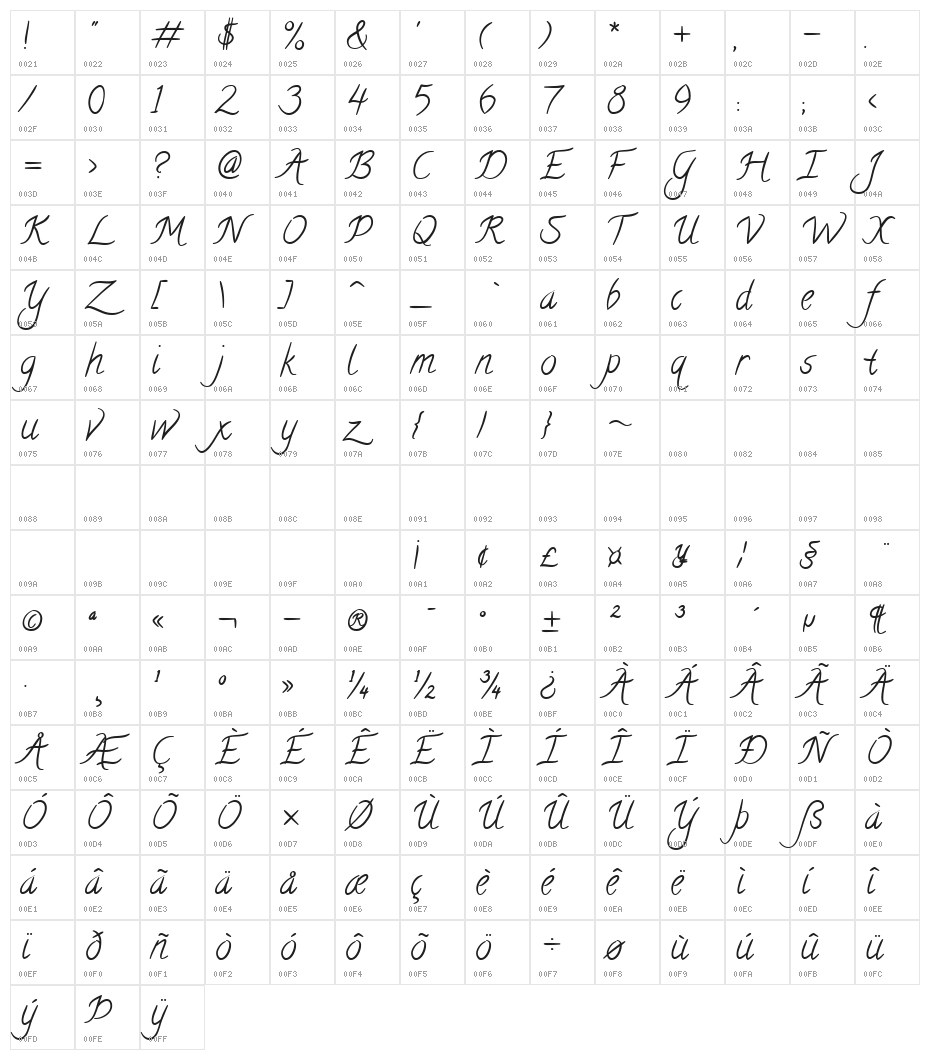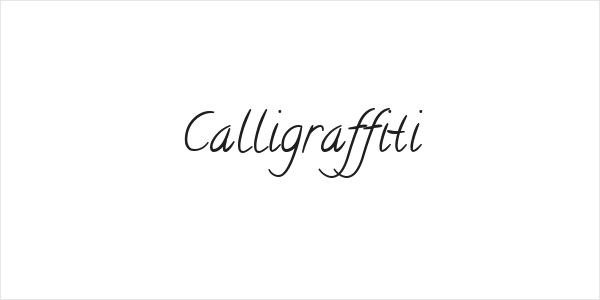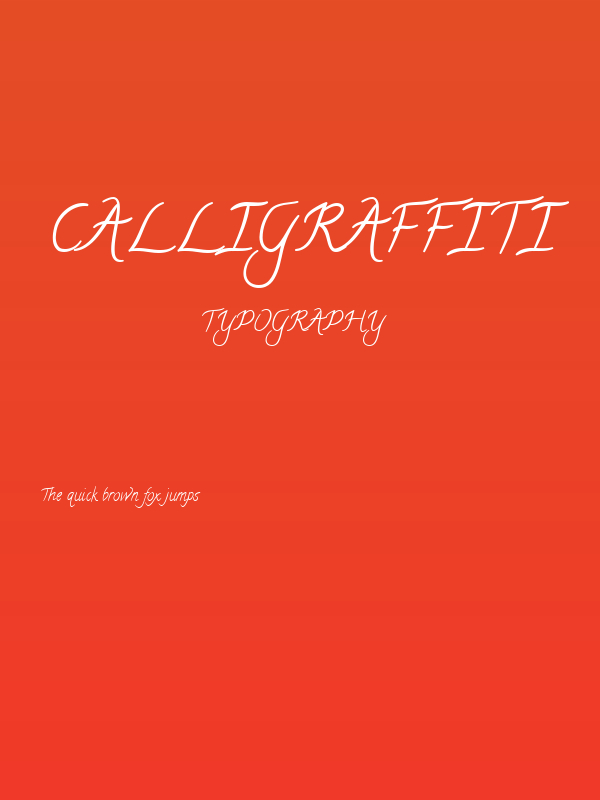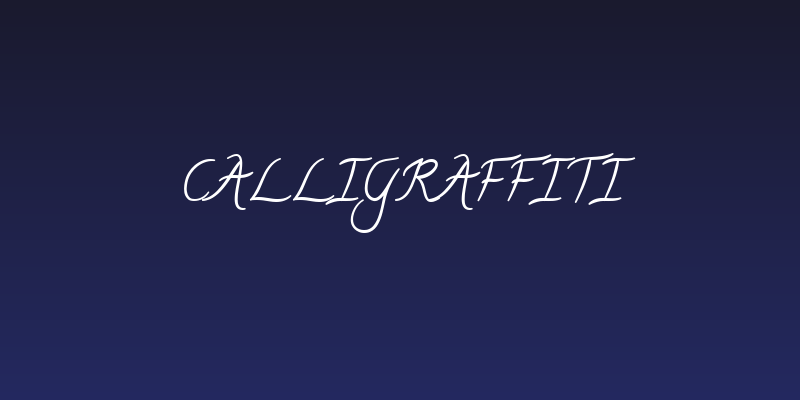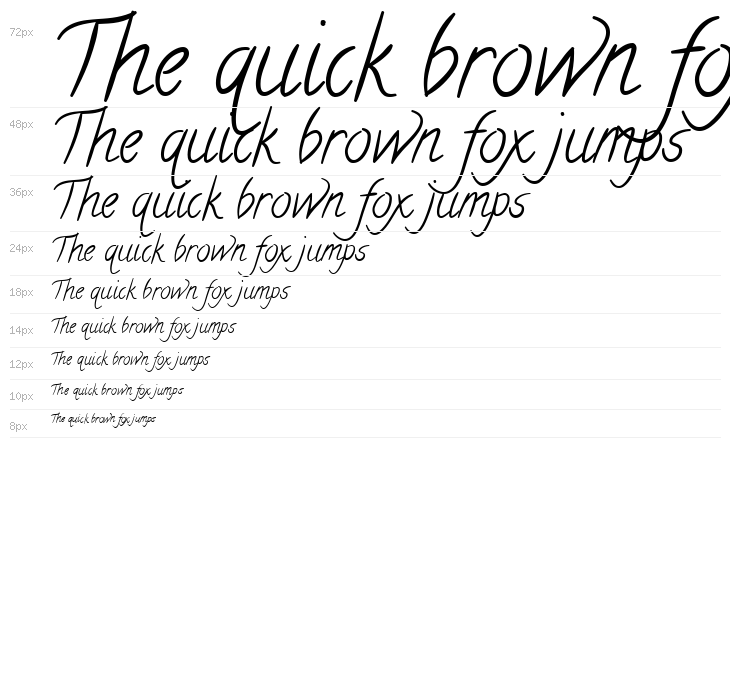
Calligraffiti Font
✎ Calligraphic
| Kategorien | Calligraphic |
| Gesamtstil | Modern, Decorative |
| Anwendungsfall | Logos, Artistic projects, Invitations |
| Vorgeschlagene Projekte | Ideal for creative projects such as logo design, event invitations, artistic posters, and branding materials that require a unique and expressive touch. |